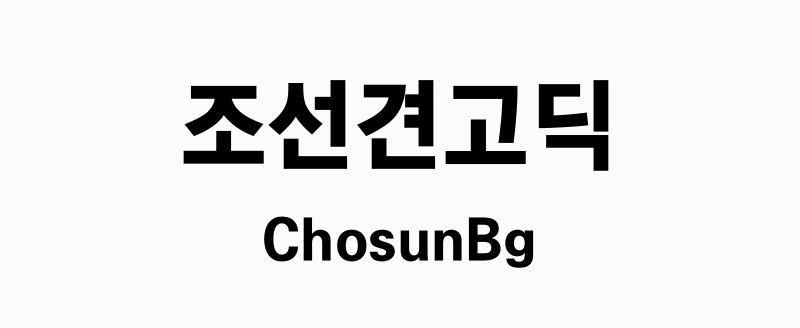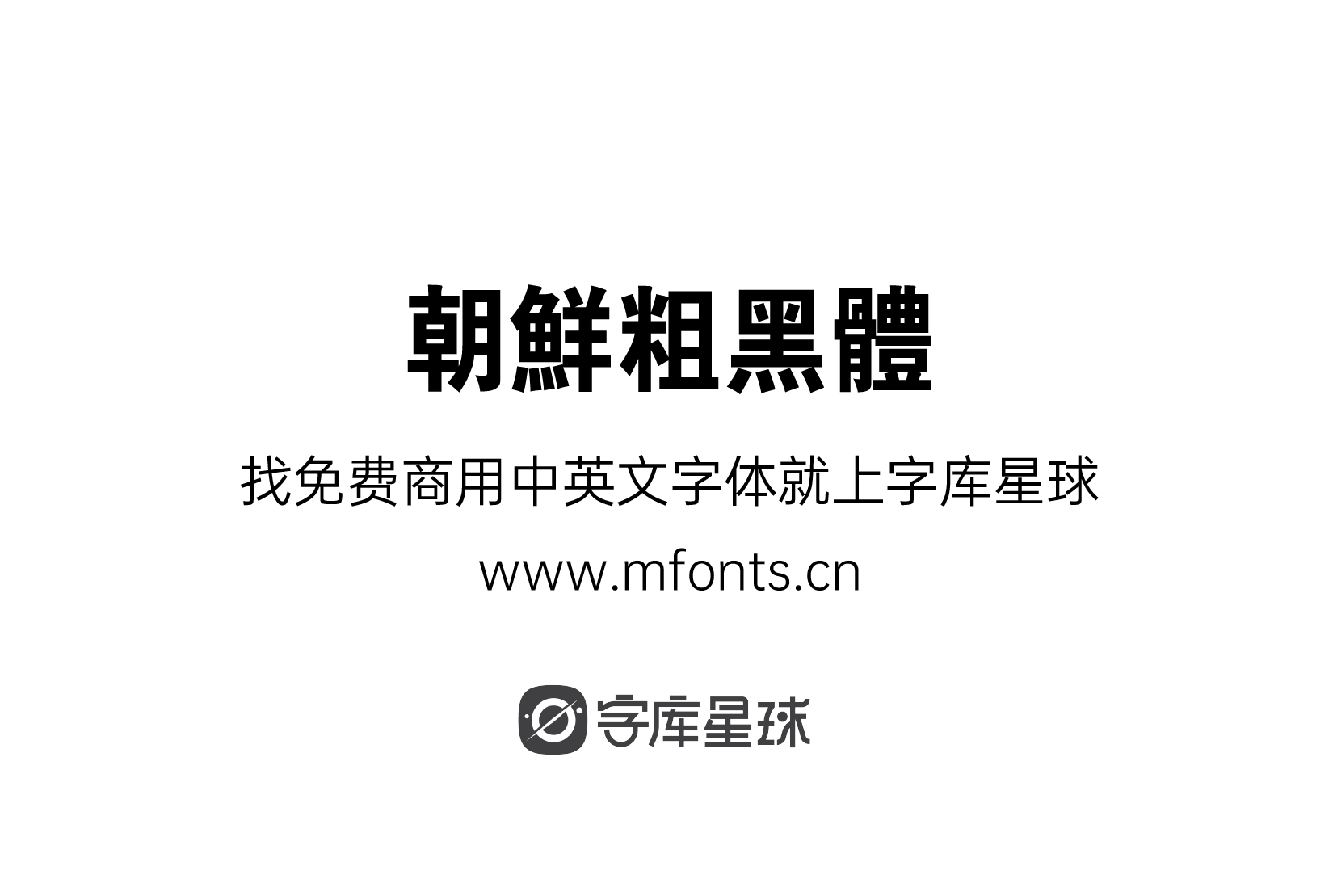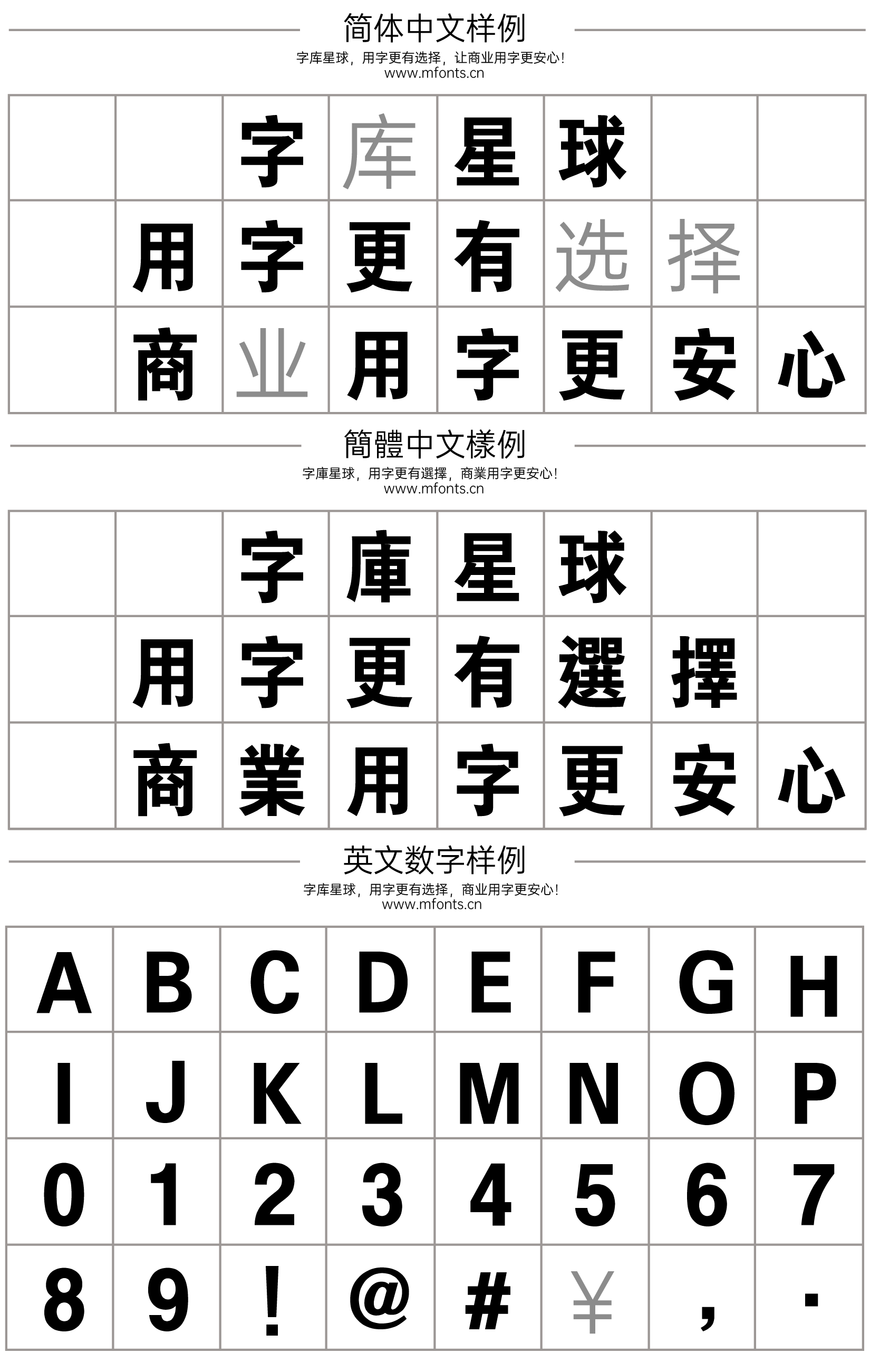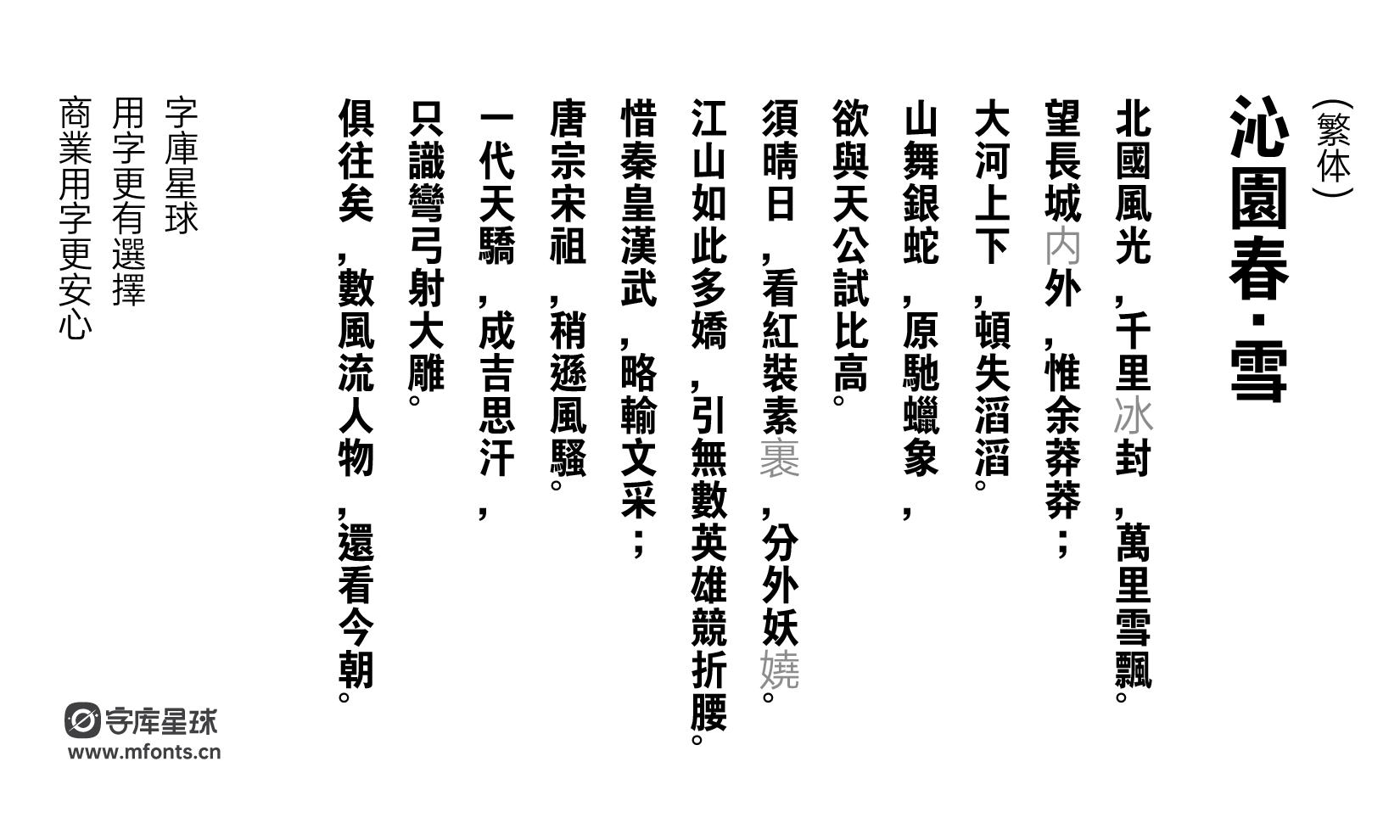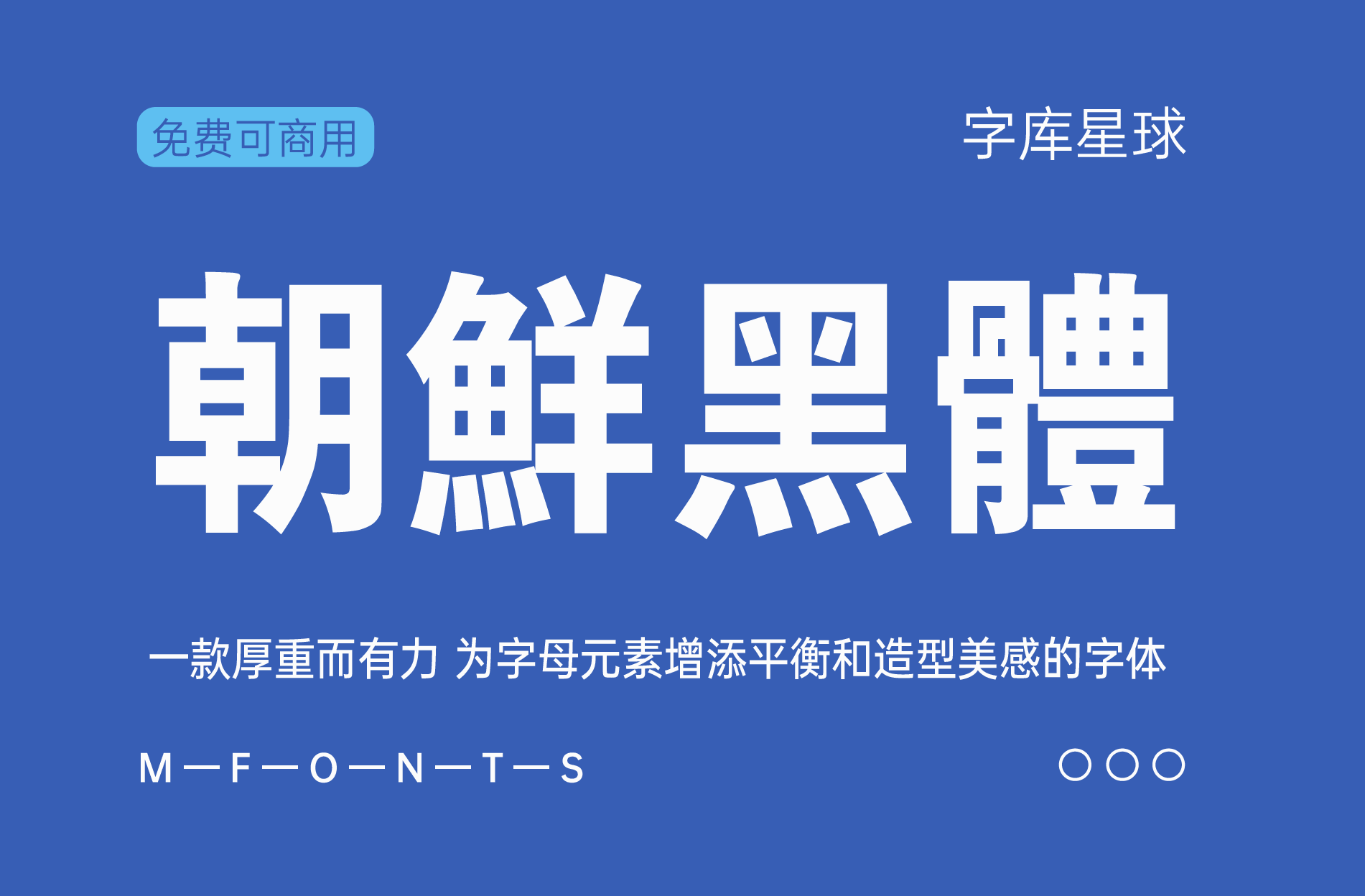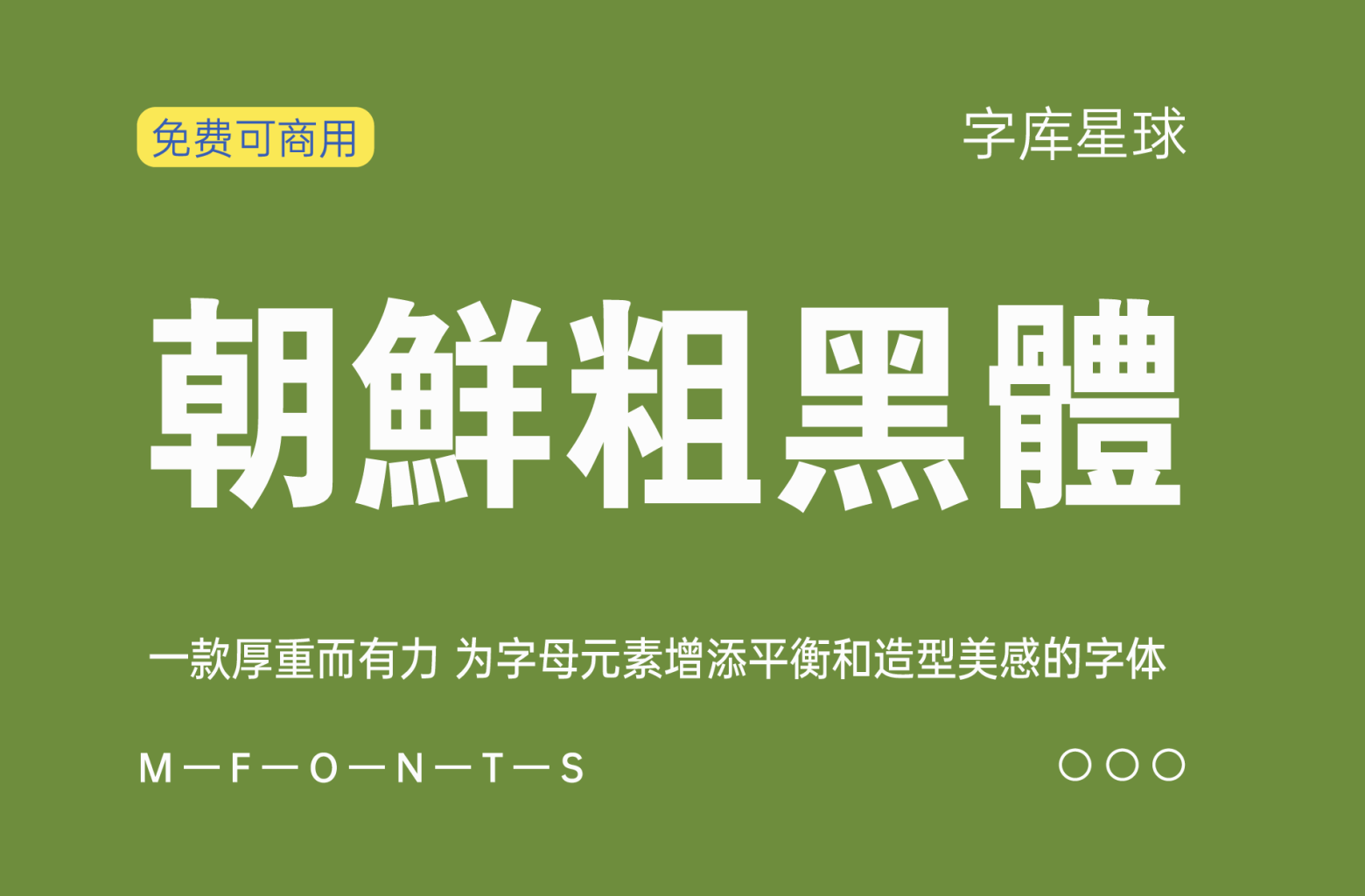
朝鲜粗黑体
朝鲜粗黑体(조선견고딕)是一种正文字体,字型较为优雅大方应用广泛的免费可商用字体,适用于正文,包装等应用。
朝鲜粗黑体是为纪念《朝鲜日报》创刊100周年的《朝鲜100年》我们免费分发“朝鲜100年字体”,这是朝鲜日报在1920年代使用的字体的现代修复版。这种字体由方日荣文化基金会开发,体现了《朝鲜日报》的精神。
朝鲜粗黑体是朝鲜日报免费发放《朝鲜日报》独家9种字体之一。